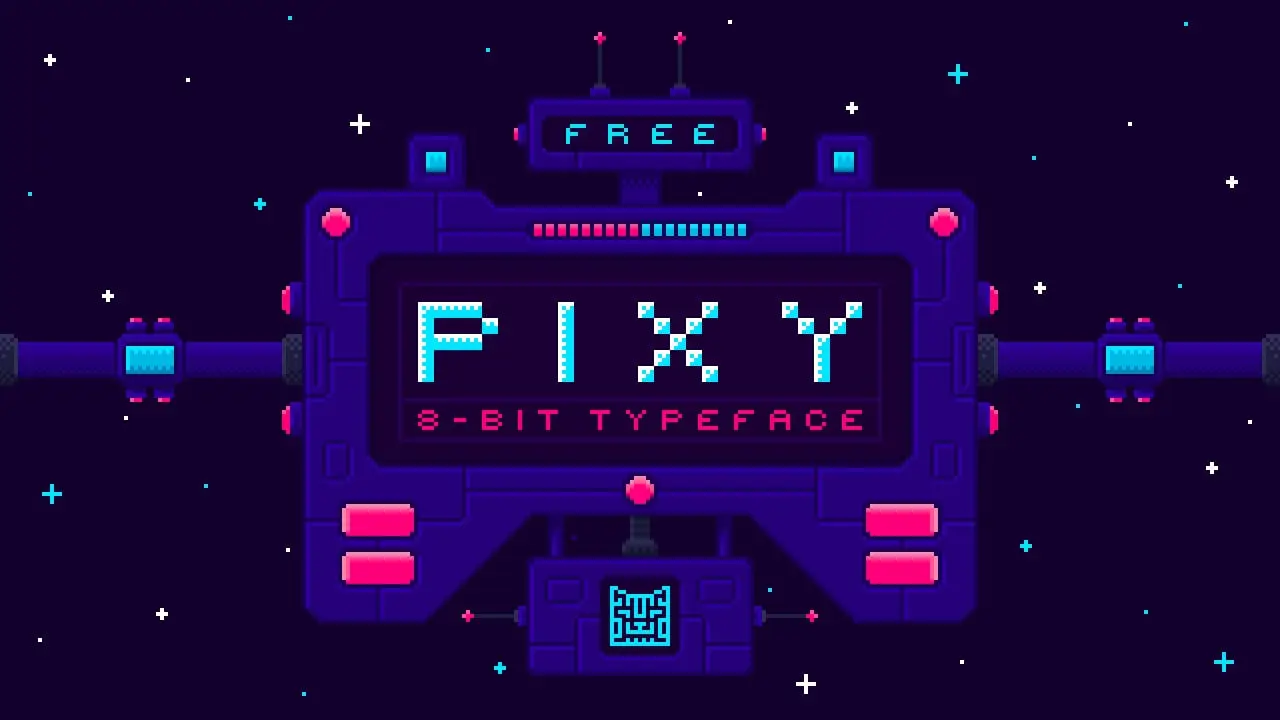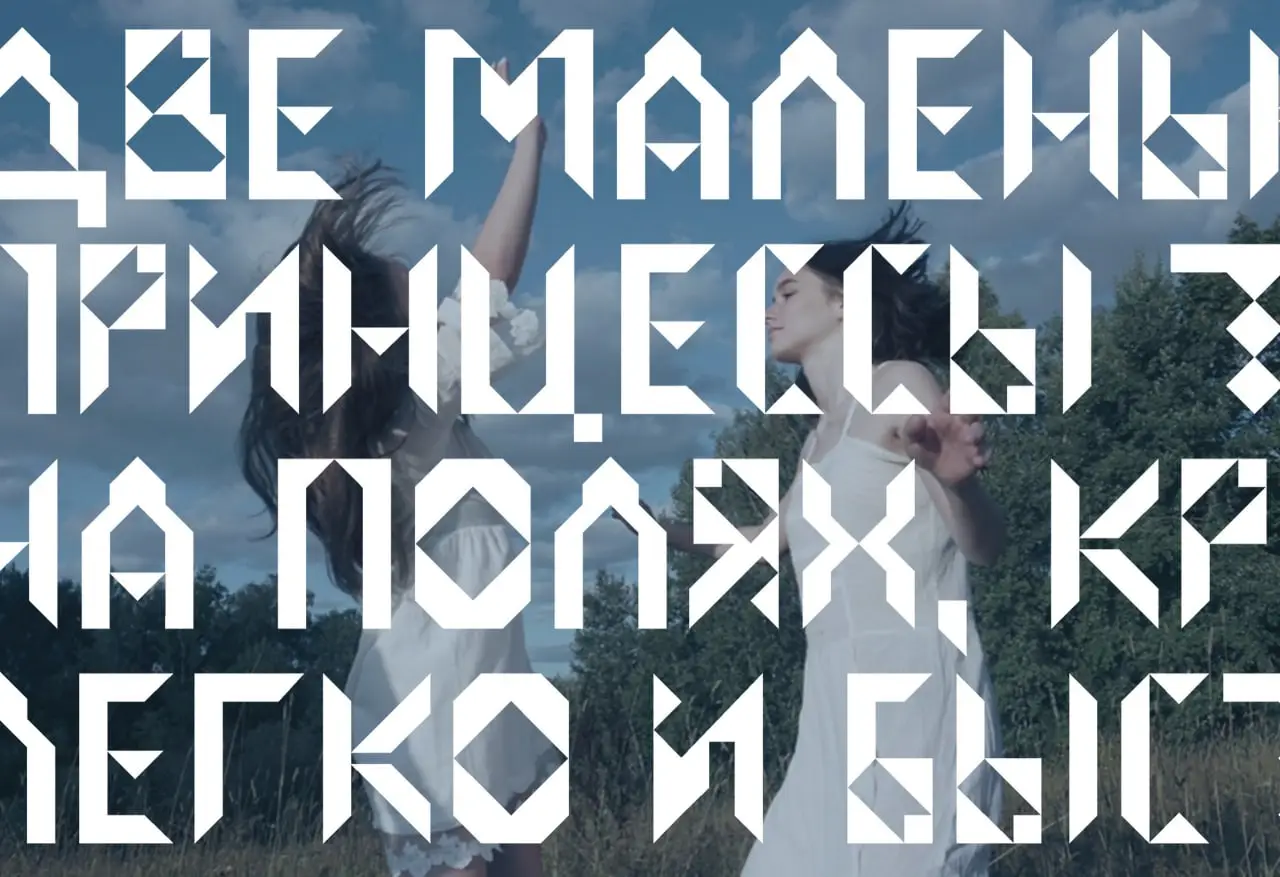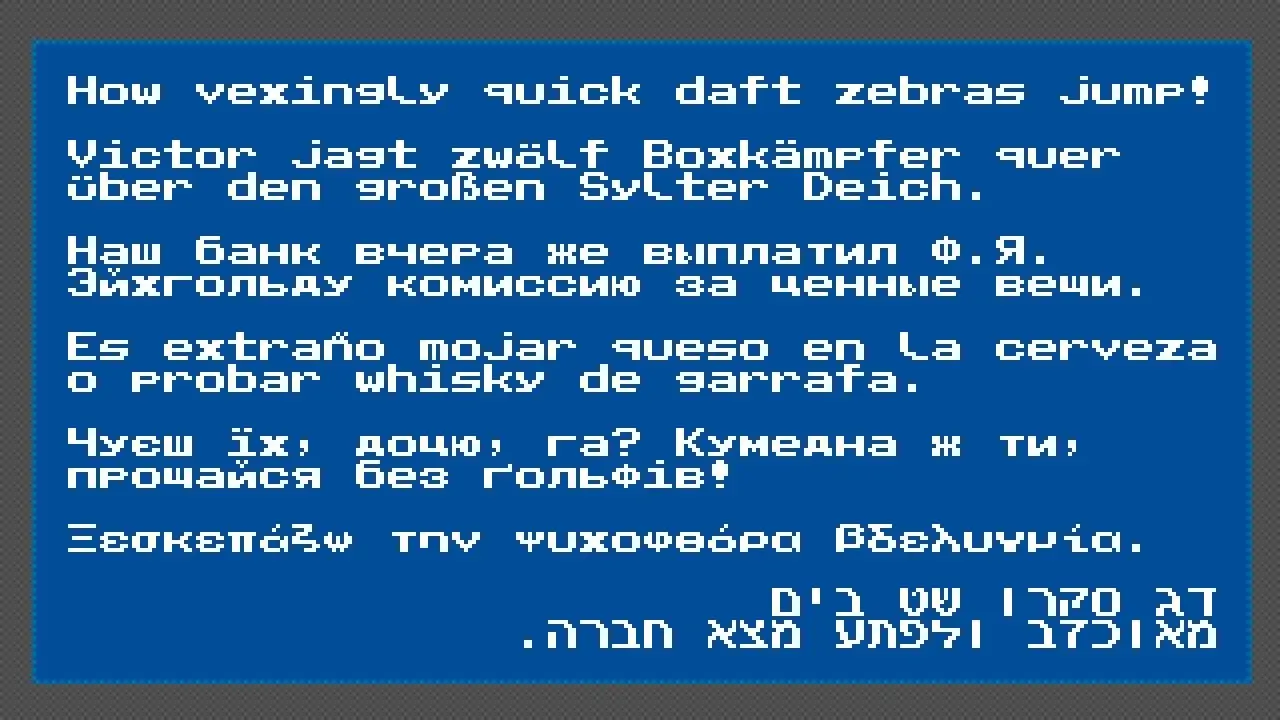
Ragfille 字体
Ragfille Font
这款华丽字体将优雅与现代感完美融合——适合品牌设计、Logo和网页创作。它用途广泛、风格时尚,提供多种字重,赋予您完全的创作掌控力!🌟
Public Pixel By Ggbot
如果你热衷游戏开发或复古风格艺术,这套像素艺术素材绝对是必备之选!它包含了大量高质量、可自定义的元素,满载纯粹的怀旧情怀。🎮👾
Paltuda 字体,由 Two Us Studio 出品
Paltuda Font By Two Us Studio
这款独特的字体系列融合了现代美学与一丝优雅,非常适合用于标志和印刷材料。提供常规体和粗体,并支持 OT 格式——您的品牌设计项目必将受益!🖋️✨
Platband 字体,由 Apollinaria Kardano 出品
Platband Font By Apollinaria Kardano
优雅与现代设计在此款简洁精致的字体中完美融合。从细体到粗体,提供OTF和TTF格式,是各类项目的百搭之选。💎
Noorge Karlos 复古优雅展示衬线字体 — 来自 Kulokale Studio
Noorge Karlos 复古优雅展示衬线字体
这款复古衬线字体尽显高雅——将传统魅力与现代风格完美融合。专为展示项目设计,提供多种字重及大小写字母。📜❤️
Prapen 超细斜体字体 By Suandana Ipandemade
Prapen Extra Light Italic
这款精致的超细斜体字型为任何设计增添了一份优雅气质。它简洁、现代且极具可读性,非常适合高端品牌和编辑工作。🌸
Paratype-Baskerville Display Pt 字体系列(扩展拉丁与西里尔字母)
Paratype-Baskerville Display Pt Font Family
经典优雅与现代多用途性在此扩展字体系列中完美融合。支持拉丁和西里尔字母,全球设计师的梦想成真!🌍📚
Okie Doko Western Slab
这款粗犷的衬线字体为您的标题和标志带来质朴的魅力与沉稳的气息。非常适合打造带有西部或冒险风格的品牌形象!🤠🔥
Prioritype-Elkoga 字体系列
Prioritype-Elkoga Font Family
一款兼具现代与经典风格的多功能字体系列,完美适用于品牌设计、标志和网页设计——多种字重为您提供无限选择。🎯
Perandory Display Type By Kulture Type
用这款醒目的展示字体大胆表达吧!其独特的字形与现代古典风格完美融合,适合在标题和海报中吸引眼球。💥
Pabs Treinta Y Seis By Pabs
一款现代、时尚的字体,极易阅读且美观悦目。非常适合品牌设计、标志制作和网页使用——简约而不失惊艳的资产。🎨
Orde Monoby Khairil Anwar
这款独特的数字设计资产将创意与功能融为一体。它品质高、用户友好,非常适合为您的项目增添一抹独特风格。🚀
Prioritype-Klemer Display
大胆与优雅在这款现代展示字体中完美融合!简洁的几何造型与多种字重,非常适合打造具有冲击力的视觉传达。💪✨
Nouvoment 展示字体
Nouvoment-Display Type
这款引人注目的展示字体以其独特的形状和大胆的风格吸引观众眼球。非常适合需要脱颖而出的宣传材料和数字内容!🌟
Microsport By Toni Setiawan
运动爱好者和品牌方,这是为你们准备的!这套高质量、主题为运动的图形素材用途广泛,可轻松集成到任何项目中。⚽🏀
Neoneon
用这套充满活力的霓虹风格图形套装点亮你的设计!高分辨率且易于定制,完美为你的作品注入现代电音氛围。💡🌈
Pixy
一套多功能的高品质设计元素,可自定义并兼容主流软件。无论新手还是专业人士都能轻松驾驭!🖌️🎉
米拉科世界 — 多尼斯·米夫塔胡丁 作品
用这套灵感满满的高品质数字设计合集,尽情释放你的创意。多样的风格让插画师和平面设计师都能得心应手。🌍✨
Neofolia 作者 Julpik Artworks
Neofolia By Julpik Artworks
沉浸在 Neofolia 精致而充满活力的插画世界中!该系列融合现代与有机元素,为您任何创意项目增添光彩。🌿🎨
Monocraft 作者 Idrees Hassan
Monocraft By Idrees Hassan
为您的品牌和数字界面注入现代气息,这套高品质设计素材包兼具灵活性与兼容性,随时助您提升作品格调!🚀🖥️